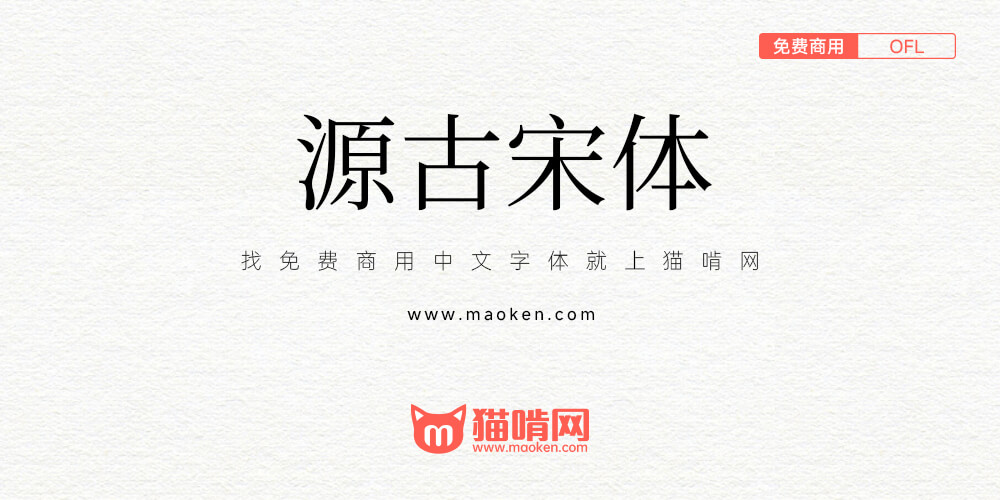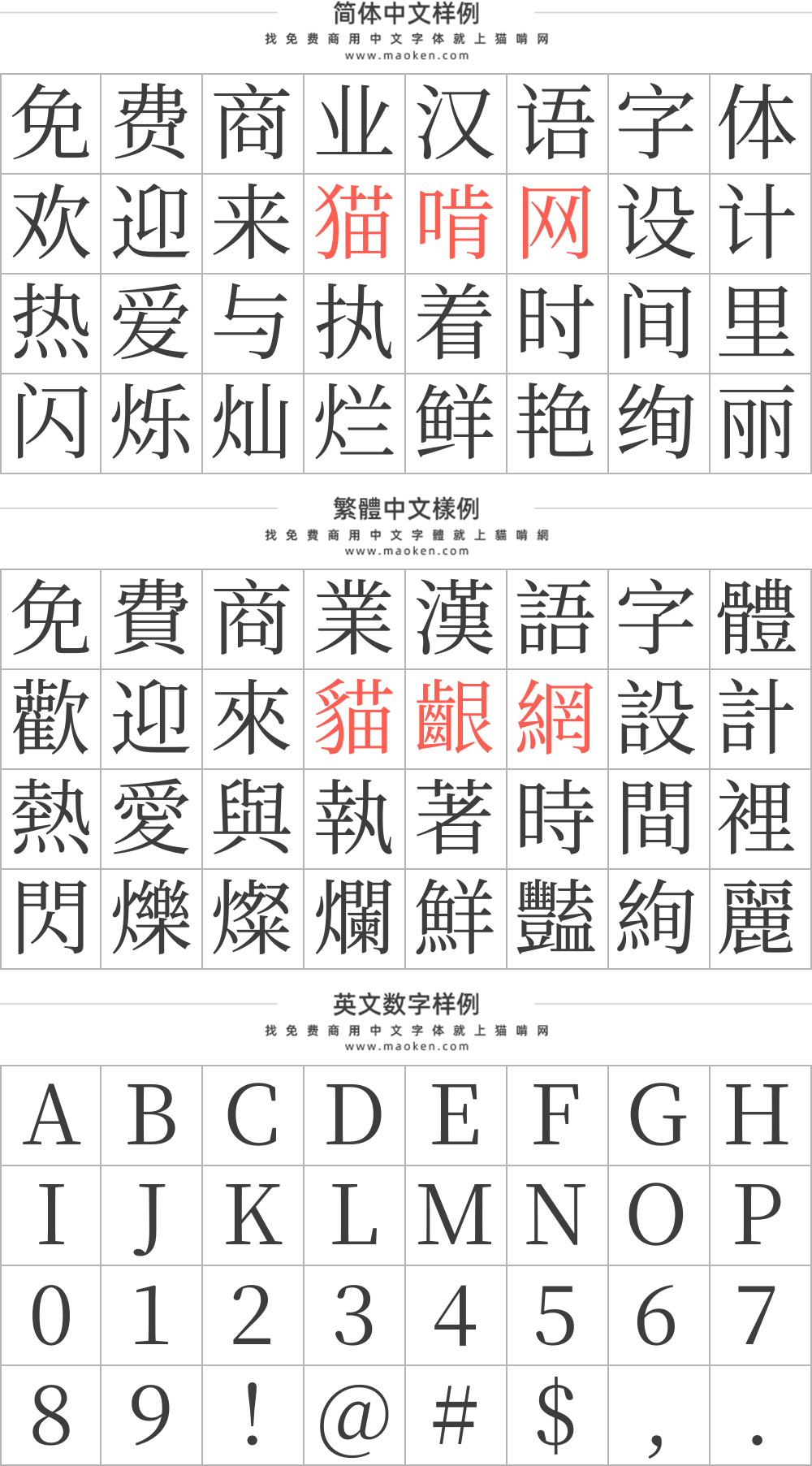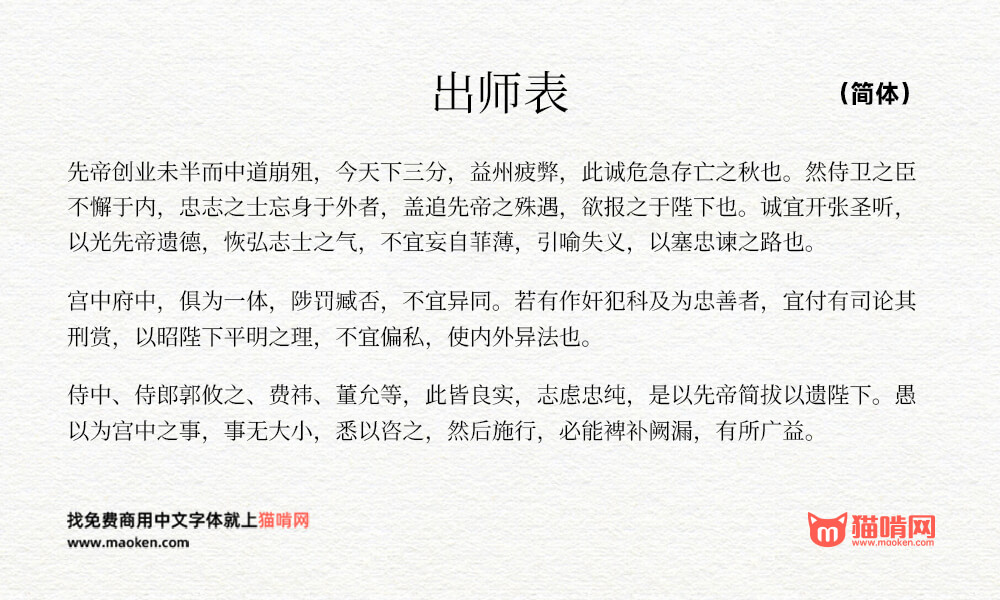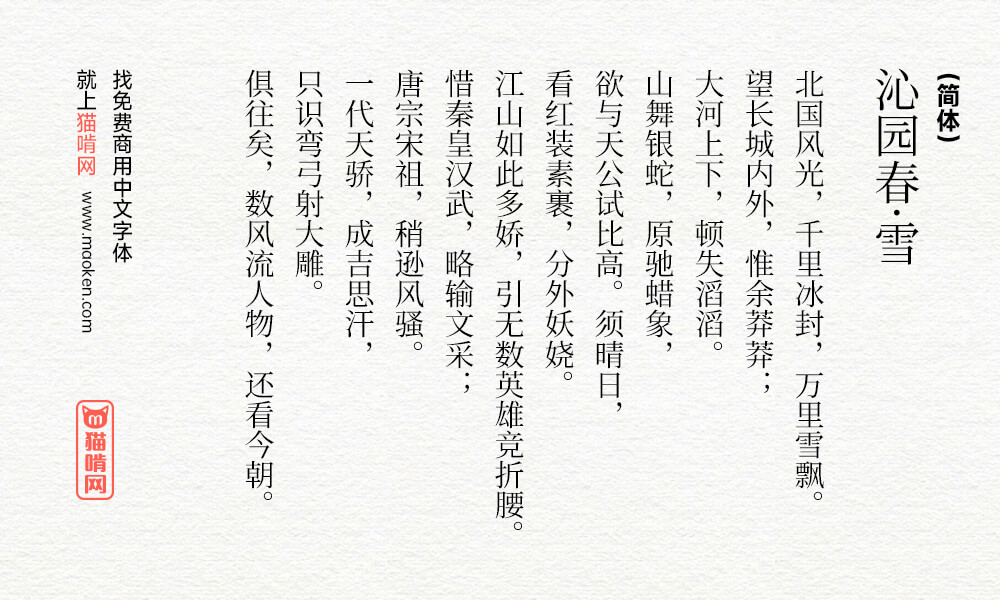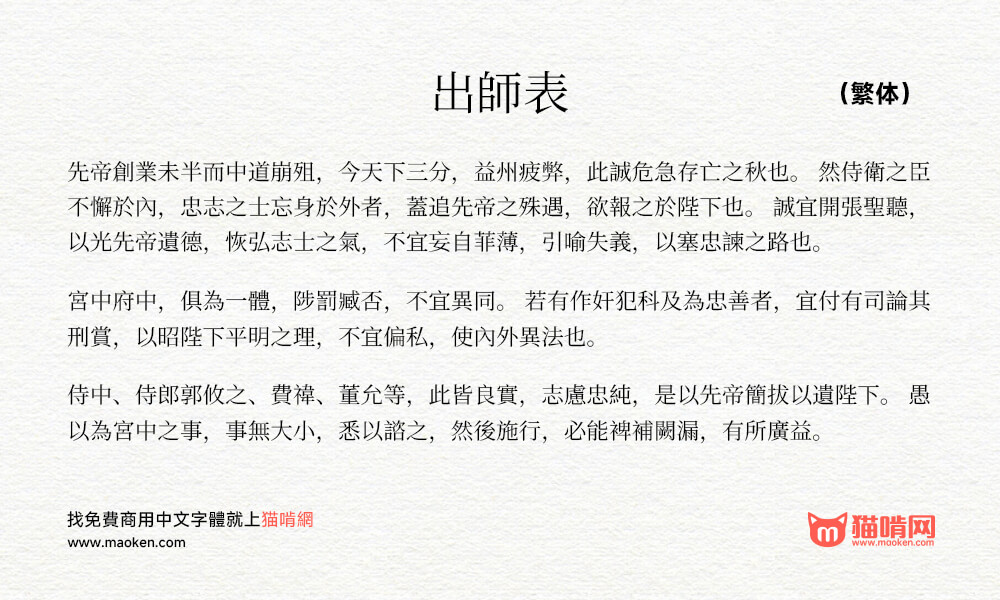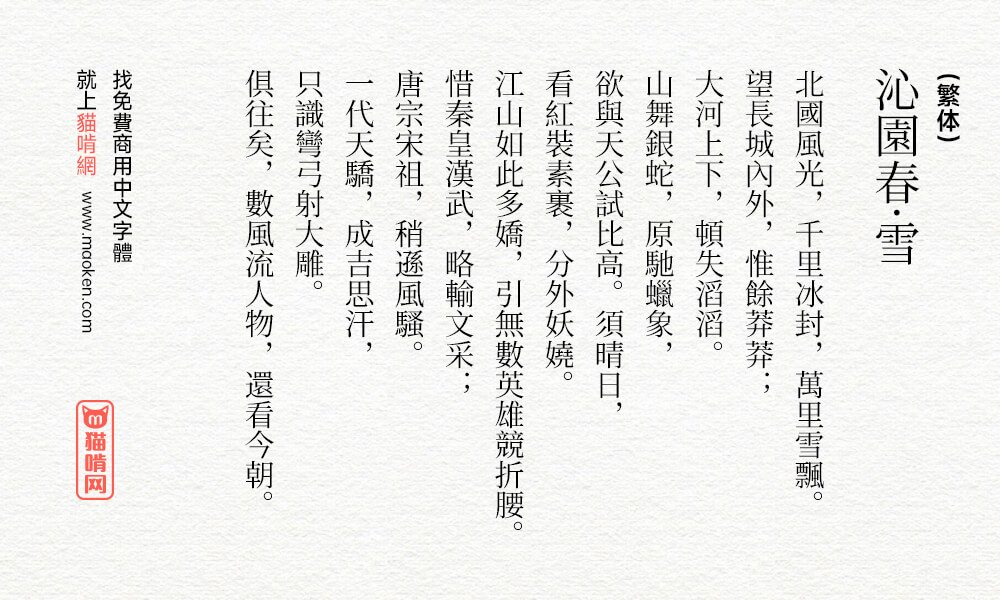
汇文系列字体的作者特里王在前段时间发布了《真·國標繁體-古籍規範字形工具包》,旨在解决《古籍印刷通用字规范》颁布后的实践断层问题。在工具包做出发布了两款古籍规范的字体源古黑体与源古宋体,黑体基于思源黑体改造,扩B区的字取自遍黑体。宋体基于思源宋体改造,扩B区的字取自文津宋体。
得益于思源丰富的地区字形,拆拆凑凑很方便就可以改出一个古籍表版本。而关于那些部件不统一的字,我有选择性地擅自进行了统一。
然后黑体和宋体各提供了两个版本,一个是仅包含古籍表表内字的纯古籍表版,一个是把古籍表外的——思源本来有的那些字一股脑放进去的“F”版本(当然这些表外字就没有按古籍表规范修改,保持思源原样)。
各位可以按需选用。日常看书写东西可以用F版,确保不缺字。
如果要作为做字体的参考或者炼丹的底子,就可以用纯古籍表版,以免被表外字误导。没错,其实这次弄这俩字体,本来就是作为炼丹工具性质的
除了这俩思源改,我的竹音仿宋和东乡明朝还在缓慢制作中,都是优先基于古籍表的构型规范做的。单独的京华老宋体古籍表版本正在调试中,后续会择日放出(坑+1)
刚才网页预览测试了一下,“櫷龜龝䆋”的风格不一样,希望修订时能更正。
感“慨”的慨字是不是不对?包括黑体里面的,当然也可能是我孤陋寡闻
这个字体就是根据 GB/Z 40637-2021 所规定的字形而调整的。